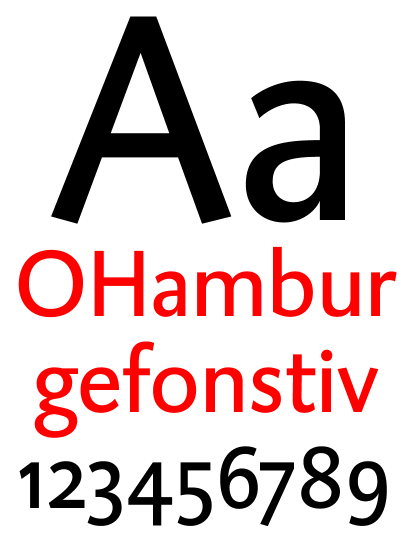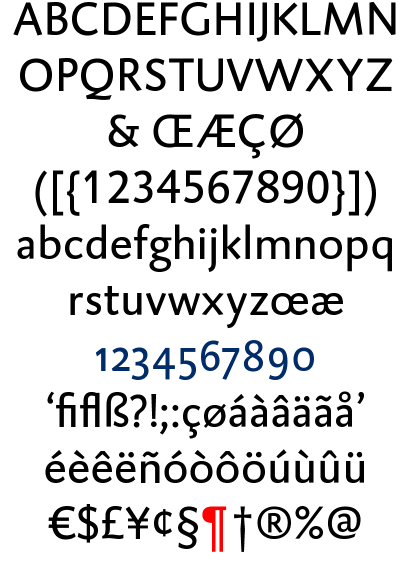
Gestaltung Briefvorlage DIN 676/5008
Mir persönlich sind die Faltstriche zu stark. Sie könnten kürzer und feiner sein (aber nicht unterschiedlich dick).
Das stimmt schon, die sind recht lang. Aber die Falzlinien werden beim Selbstausdrucken durch den weißen Rand ja noch mal ein ganzes Stück kürzer. Welche Strichstärke haben die Linien denn, Mexl916?
Ich (nur meine Meinung) würde vielleicht auf die Lochmarke ganz verzichten, die braucht man heutzutage nämlich nicht mehr wirklich – die meisten Locher haben eine Führungsschiene, die für die Lochung an der korrekten Stelle sorgt. :-) Streng genommen kann man auch auf die untere Falzmarke verzichten, da sich die Positionierung dieser Falz aus der oberen Falz ergibt.
... Streng genommen kann man auch auf die untere Falzmarke verzichten, da sich die Positionierung dieser Falz aus der oberen Falz ergibt.
Das hätte ich auch schon geschrieben, wollte aber nicht das Thema durcheinander bringen.
Lochermarken finde ich nicht verkehrt, da ich zumindest noch so ein altes kleines Teil ohne Schiene habe. Aber das muss man eben abwägen.
Ich kann mir nicht helfen, aber mir gefällt die Minion für einen Brief nicht. Ich würde, so platt wie's ist, entweder eine 'schreibmaschinenartige' Schrift oder eine Grotesk bevorzugen.
Nicht? Ich kehre mit schönster Regelmäßigkeit wieder zur Minion zurück. Insbesondere bei den Serifenlosen habe ich immer wieder wilde Phasen in denen ich alles Mögliche ausprobiere nur um dann festzustellen daß es irgendwie nicht sonderlich gut funktioniert. Ich habe einige Kandidaten bei denen der erste Eindruck durchaus so ist wie ich ihn mir vorstelle. Wenn das dann aber mehr Text als nur ein Absatz ist, dann verleidet es mir das Lesen, selbst wenn ich mir beim Satz noch so viel Mühe gebe. Die Minion ist dann in jedem Fall eine robuste Notlösung.
»Schreibmaschinenartige« finde ich ganz persönlich konzeptionell doof. Habe das auch noch nie verstehen können. In meiner Jugendzeit wurden die tatsächlich noch verwendet; mit Schreibmaschine geschriebene Briefe waren ungeheuer formell vom Eindruck her. Oftmals wird ja der »persönliche touch« angeführt – das funktioniert bei mir daher schon gleich gar nicht. Und was soll sonst der Vorteil sein?
Nach der perfekten Korrespondenzschrift suche ich noch …
»Schreibmaschinenartige« finde ich ganz persönlich konzeptionell doof. Habe das auch noch nie verstehen können. In meiner Jugendzeit wurden die tatsächlich noch verwendet; mit Schreibmaschine geschriebene Briefe waren ungeheuer formell vom Eindruck her.
Früher mögen Schreibmaschinenschriften formell gewirkt haben — heute ist doch eher das Gegenteil der Fall. Behörden und viele Firmen schreiben ihre Briefe aus der Times, Schreibmaschinen benutzen bloß noch Privatleute. Wer mit der Schreibmaschine tippt, nimmt sich die Zeit, für jemanden persönlich einen Brief zu tippen, und nicht bloß in einer Word-Vorlage den Empfänger einzusetzen. Während die Times und ähnliche Antiquas (und die Minion ist nun mal ziemlich ähnlich) daher für mich immer wie Behörden- und Serienbriefe aussehen, wirken schreibmaschinenähnliche Schriften viel persönlicher.
[…] heute ist doch eher das Gegenteil der Fall.
Diejenigen die Schreibmaschinen noch kennen werden sie auch formal einstufen und die jüngere Generation weiß im Grunde schon nicht mehr, wie ein echt in Schreibmaschine geschriebener Brief aussieht. Ich habe selber gerade die Rarität gehabt, daß mir jemand ein 30seitiges mit der Maschine geschriebenes Manuskript zugeschickt hat. Ich war perplex wie »unordentlich« das im Vergleich doch aussieht und habe tatsächlich nachgeschlagen und gesehen, daß meine alten Dokumente auch so ausgesehen haben. Davon ausgehend muß ich Dir insofern recht geben als daß ein Brief der in einer Schreibmaschinenschrift gesetzt ist im Prinzip wenig mit einem Brief der tatsächlich mit der Schreibmaschine geschrieben wurde gemeinsam hat. Das Schriftstück bekommt dann quasi eine etwas »historische« Anmutung.
Ich persönlich kann trotzdem nicht verstehen, warum das »persönlich« wahrgenommen wird, aber das ist ja mein Privatvergnügen! :nicken:
Und dann ist ja auch immer noch die Frage, ob man z.B. einem Geschäftsbrief (gerade wenn er auf der DIN beruht) überhaupt eine persönliche Note geben sollte. Das ist so wie bei Bewerbungsfotos. Vor langen Jahren gab es mal die verbreitete Meinung quasi private Fotos von sich auf die Bewerbung zu kleben. So nach dem Motto: »Ich will mich doch so präsentieren wie ich im normalen Leben bin und nicht so ›künstlich‹ und steif in Anzug und Krawatte«. Irgendwann habe ich darüber mal mit der Bewerbungsberaterin hier an der Uni gesprochen – die wäre fast rücklings vom Stuhl gefallen vor lachen. Konzeptionell ist das nämlich auch Blödsinn: eine Bewerbung ist nun mal ein formaler Prozeß der soviel mit »Natürlichkeit im normalen Umfeld« zu tun wie ein Kuckuck mit einem Känguru. Dahin gehört eben auch einfach ein nicht nur gepflegtes sondern auch formales äußeres Erscheinungsbild.
Ein Geschäftsbrief muß für mich in erster Linie gut lesbar, recht sachlich und einigermaßen neutral bis freundlich sein. Für einen gelungenen »persönlichen touch im DIN-Format« (sic) muß jemand schon eine glückliche Hand und ein gutes Auge haben, ansonsten beäuge ich persönlich das eher skeptisch.
Ich schweife aber glaube ich gerade doch etwas ab ... :-|
Und dann ist ja auch immer noch die Frage, ob man z.B. einem Geschäftsbrief (gerade wenn er auf der DIN beruht) überhaupt eine persönliche Note geben sollte.
Ich dachte, es geht hier um Privatpost? Meine Empfehlung und Vorliebe für schreibmaschinenartige Schriften bezieht sich nur darauf.
Es geht zwar um Privatpost, aber ja nicht um private Briefwechsel, sondern eher um Schriftwechsel mit Behörden, Institutionen, Firmen und eventuell auch um Bewerbungsschreiben an potenzielle Arbeitgeber. Da fände ich eine Schreibmaschinenschrift zu tendenziell.
Hast Du von der Schrift zufällig ein paar Absätze Blindtext parat? Ihr zwei habt mich jetzt doch neugierig gemacht, wie die Schrift als Fließtext wirkt. :-)
Ist das hier nicht sogar in der hübschen gesetzt?